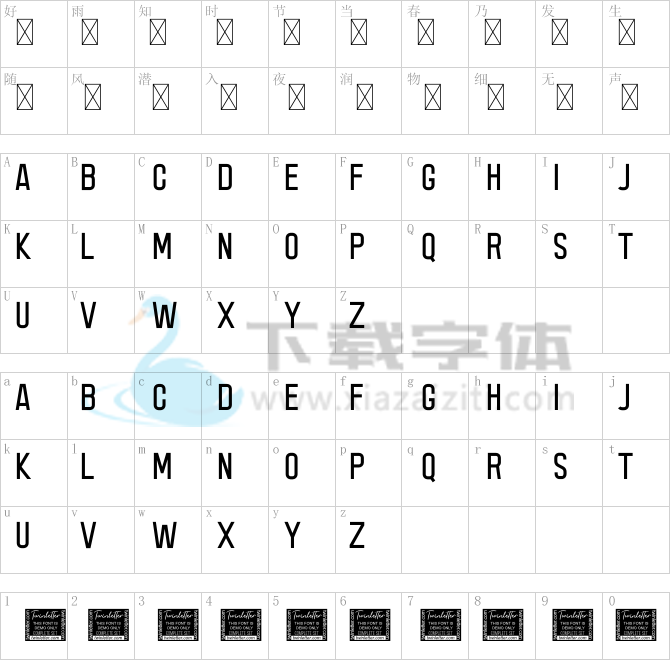
Acmatic Thin Personal.otf字体下载
Acmatic Thin Personal.otf字体下载,这款字体结构工整、笔画清晰,兼顾美观与易读性,适用于标题、正文、海报、包装、LOGO 等多种场景。字形优雅稳定,风格百搭耐看,适配日常排版与创意设计,让文字呈现更舒适、更具质感。Acmatic Thin Personal.otf字体下载一笔一画,皆是细节,以均衡的比例、流畅的线条打造舒适视觉体验,字形端正大气,风格简约现代。无论是商业设计、品牌宣传还是日常排版,都能轻松驾驭,让文字更有格调与力量。Acmatic Thin Personal.otf字体下载字体下载。